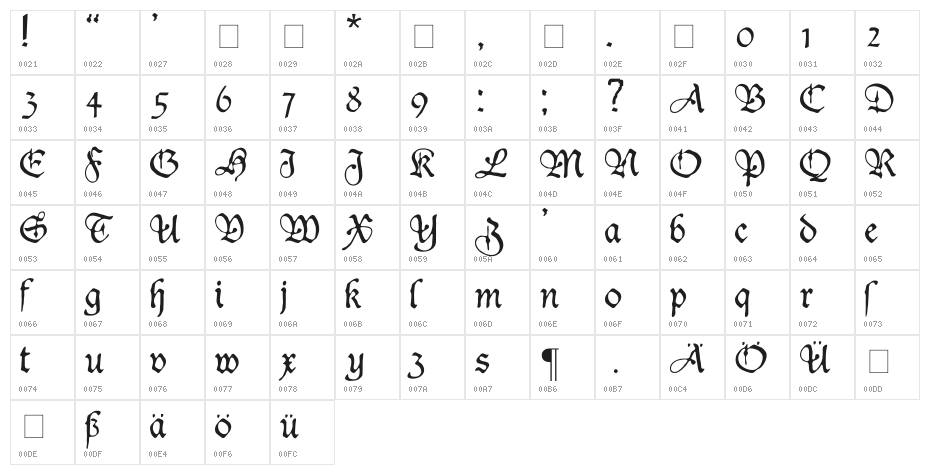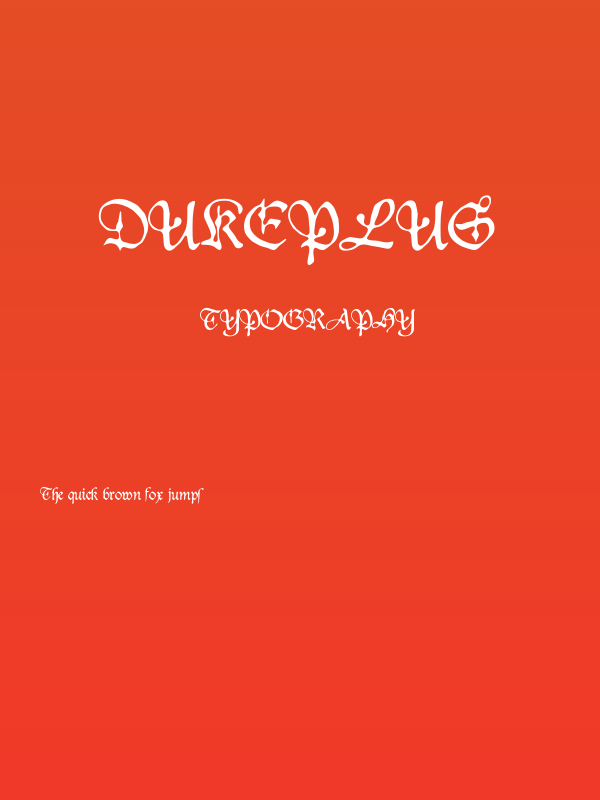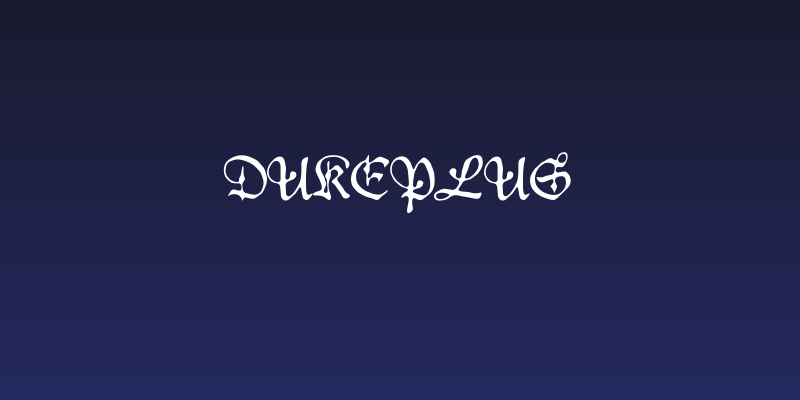
Dukeplus Font
✎ Calligraphic
| Progetti proposti | Suitable for wedding invitations, historical documents, certificates, and branding that requires a vintage touch. |